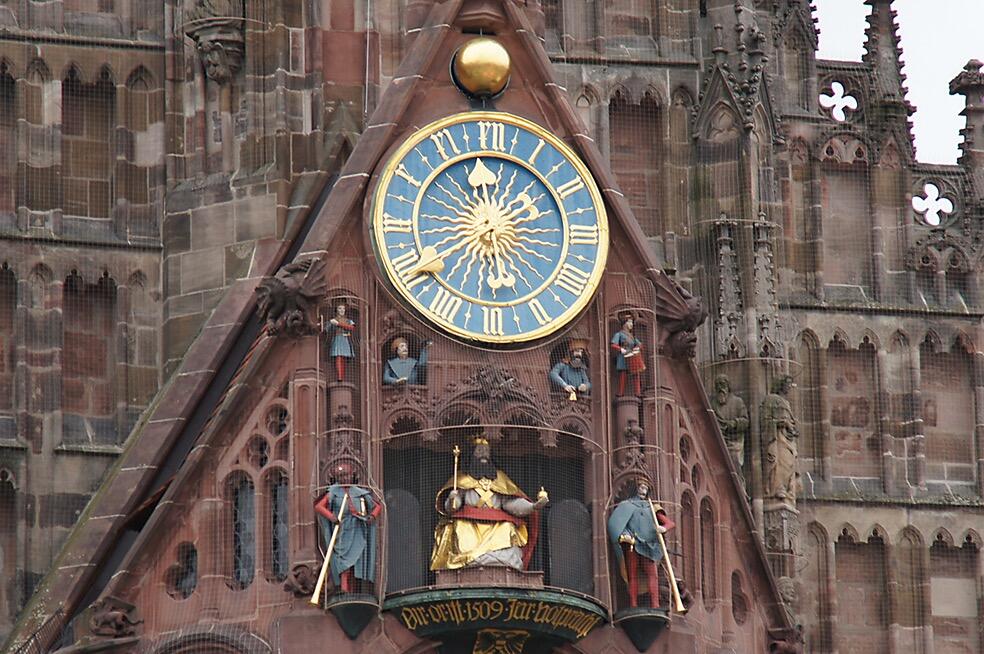
Römische Ziffern unter gothischen Schriften
ich bin über diesen Flyer gestolpert und das "Part IV" fiel mir sofort ins Auge.
Fühlt sich falsch an, aber vielleicht irre ich mich ja.
Meine Frage: Gibt es Regeln zur Verwendung römischer Ziffern in gebrochenen Schriften?
Wurden die überhaupt eingesetzt?
Das sieht logisch aus. Römische Zahlen bedeuten Latein und damit Antiqua.
Es gibt Ausnahmen.